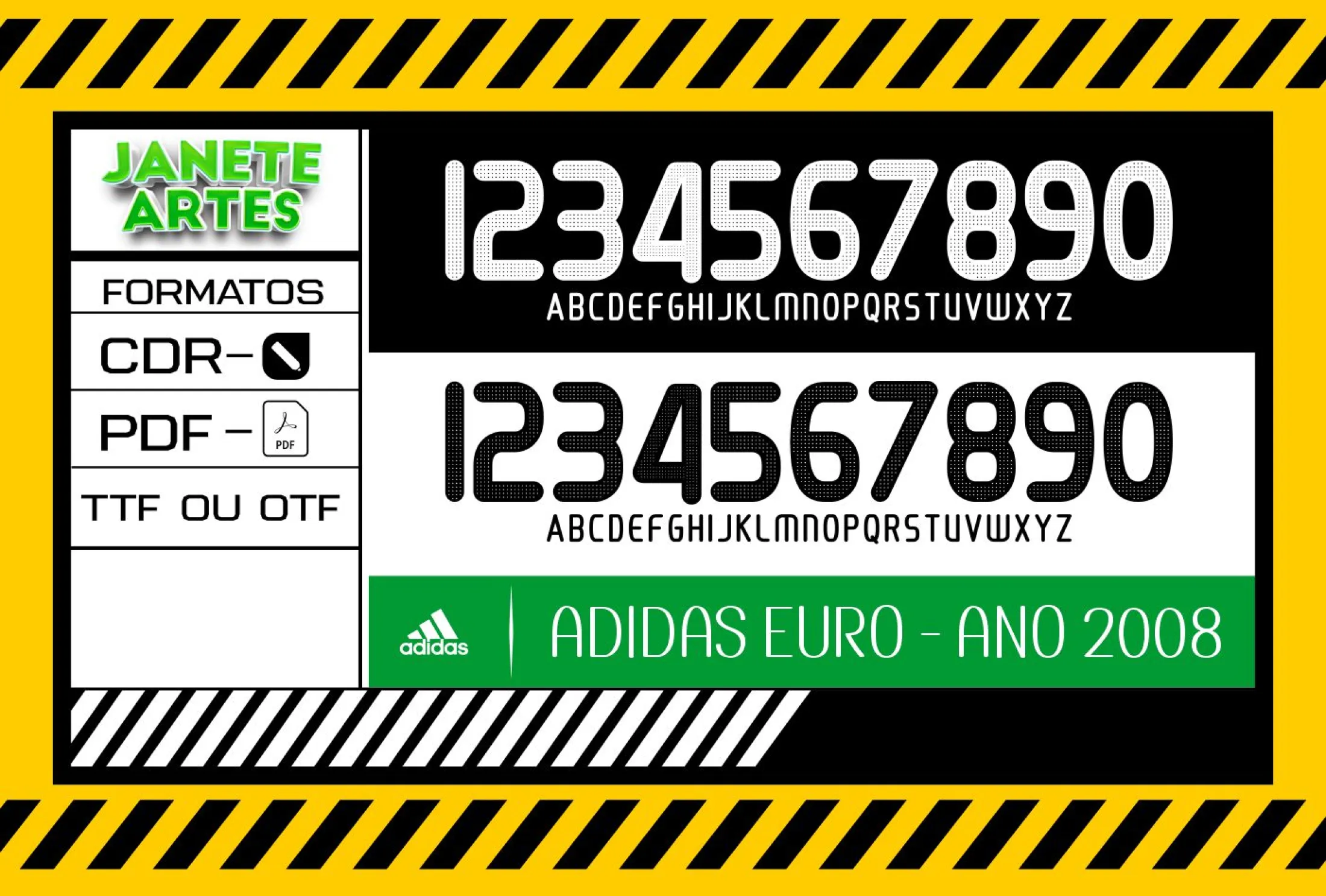
Fonte de Time Tipografia Adidas 2008
Uma história que conecta paixão e estilo
Imagina a alegria do Mateus, um jovem torcedor fanático, que sempre sonhou em ter uma camisa exclusiva com a fonte do seu time preferido, de 2008, aquela tipografia icônica da Adidas que marcou uma era. Ele descobriu o Arte Fonte Time Tipografia Adidas 2008, aquele arquivo que trouxe vida ao seu sonho. Criou camisetas para o grupo da torcida, virou destaque nos campeonatos amadores e ainda recebeu elogios por sua originalidade. É o poder de um design único que conecta gerações e emoções.
- Design exclusivo da fonte original do time, versão Adidas 2008
Este arquivo é perfeito para criar desde camisetas para torcidas organizadas até para eventos esportivos ou festas temáticas. Também é um presente criativo para quem ama futebol e design.
- Camisetas pretas com a fonte branca destacam o design clássico
- Camisetas brancas valorizam o contraste e dão um ar esportivo